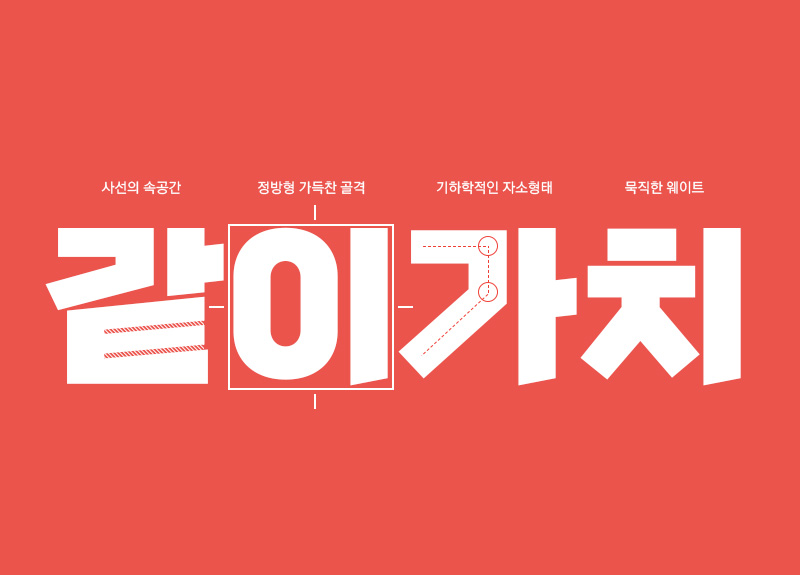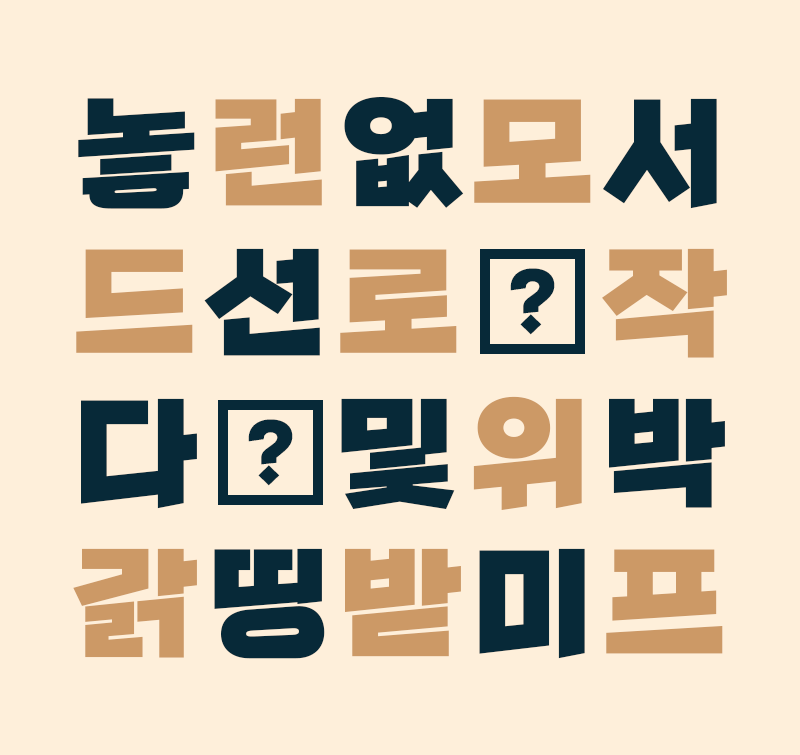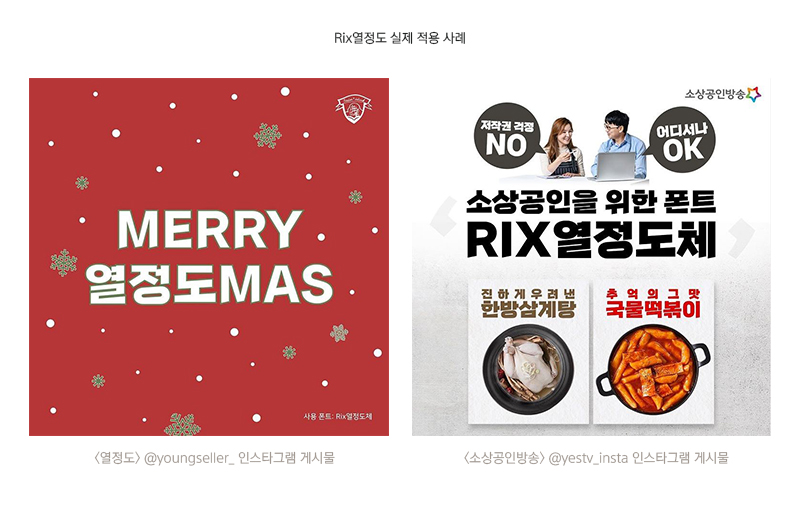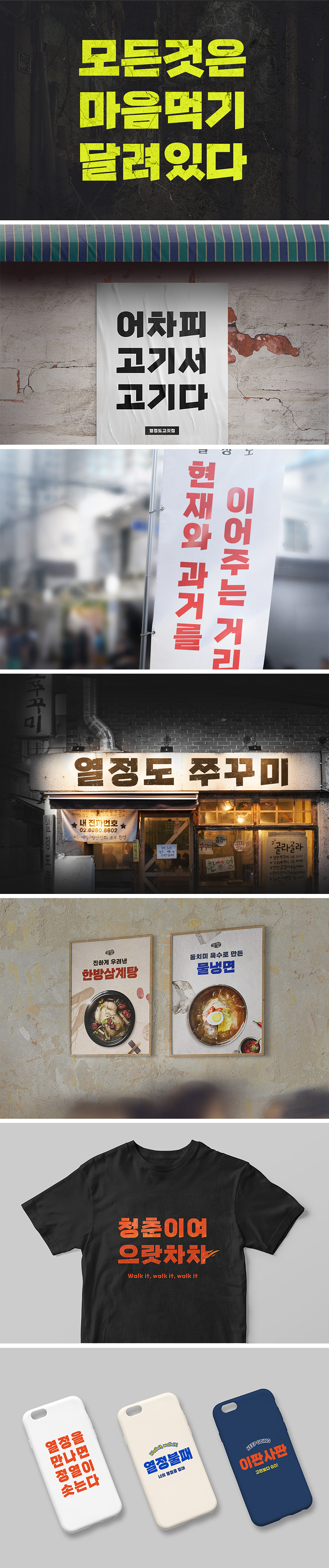
Rix열정도
정방형의 꽉 찬 골격으로 묵직하지만 날렵한 사선의 획이 속도감 있는 서체입니다.
과거와 현재를 잇는 열정도 거리처럼 상반된 특징이 조화롭게 어우러진 제목용 글꼴입니다.
꽃처럼 피어나 별처럼 빛나는 그대에게
열정도체는 느리고 듬직합니다. 투박하고 복고적입니다.
열정도체는 빠르고 날렵합니다. 경쾌하고 세련되어 현대적입니다.
열정도체는 상반된 두 특징이 조화롭게 섞인 독특한 매력의 서체입니다.